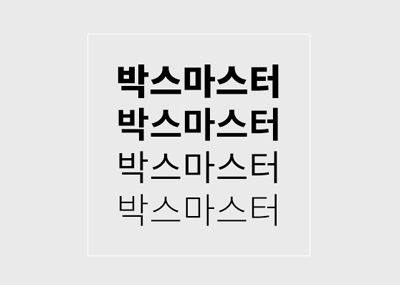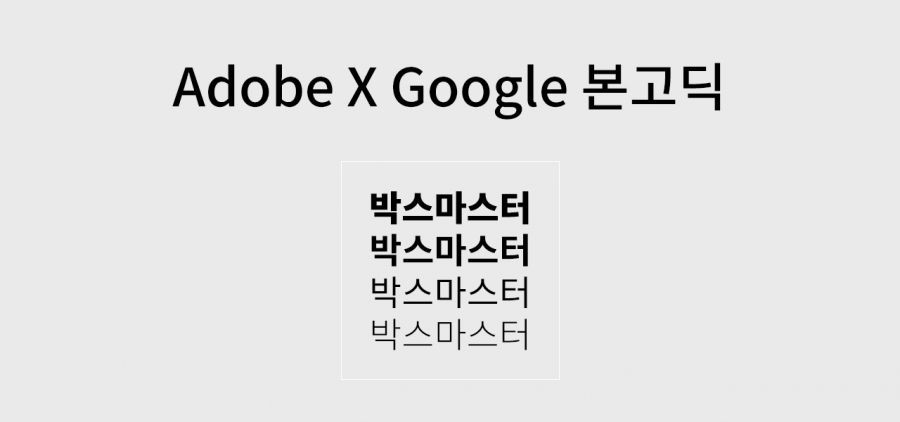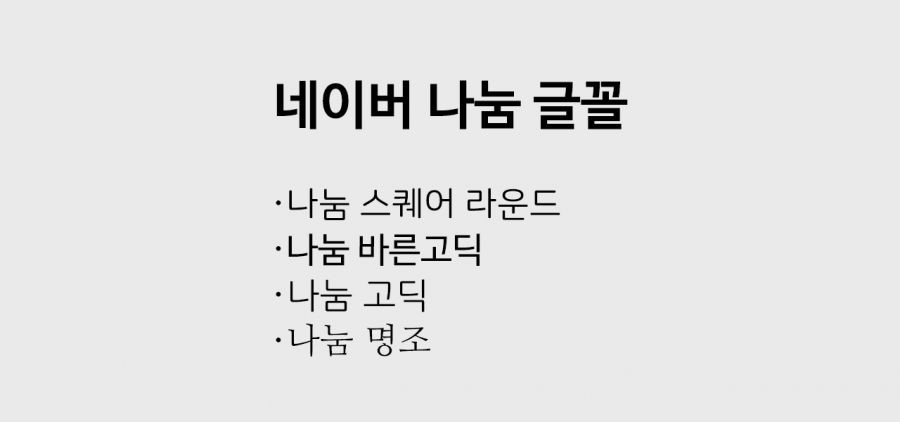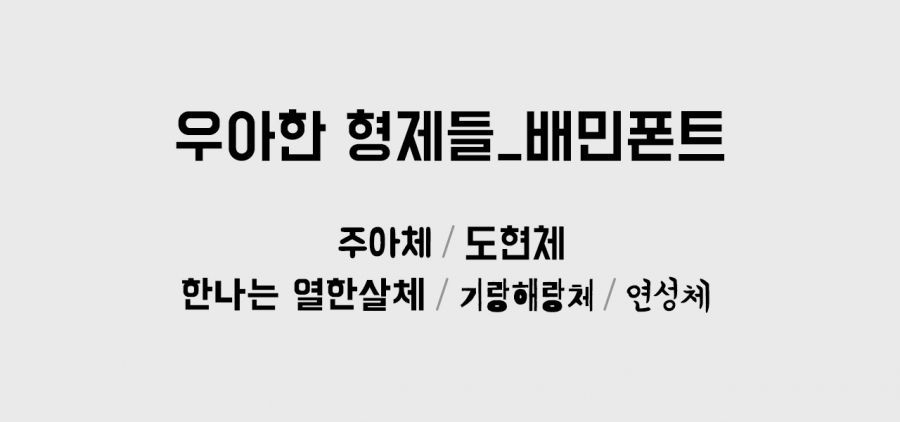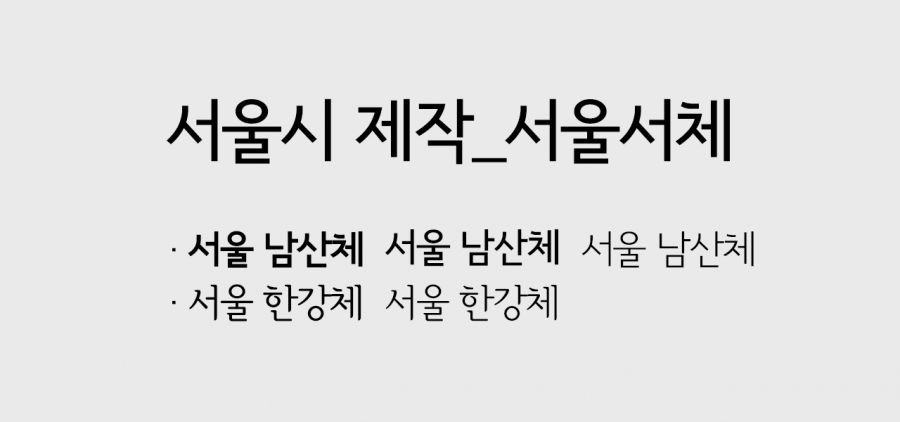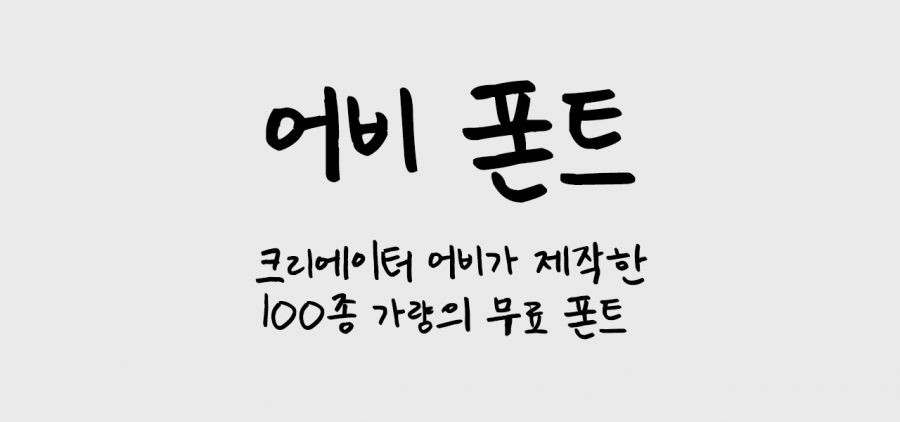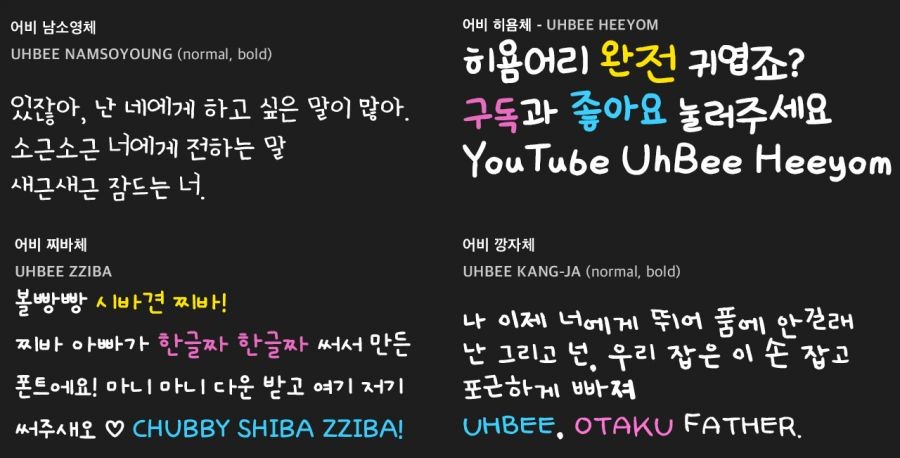
무료 폰트 똑똑하게
활용하기
서체는 브랜드의 인상과 감성을 좌우!
"글씨를 잘 쓰는사람이 마음씨도 곱다" 라는 말 들어보셨나요?
"삐뚤삐뚤한 글씨는 마음가짐도 삐뚤어지게 한다"는 말도 들어보셨을거예요. 디지털 시대가 도래하면서 손으로 글씨를 적을 일이 과거에 비해 현저히 줄어들었지만 우리는 과거부터 예쁘고 보기좋은 서체를 권장하고 찾아왔습니다. 아무리 좋은 글이라도 보는이가 자연스럽게 읽히지 않는다면 말하고자하는 의미가 전달되지 않겠죠?
디자인에서도 어떤 서체를 사용하느냐에 따라 경쾌함,차분함,진지함,신뢰성 등 서체에서 전해지는 감성을 이해하고 적절하게 사용해 대중들에게 기업이 전하고자 하는 바를 명확하게 전달하는것이 좋은 디자인이라고 할수 있겠습니다. 또, 기업이 가진 성격이나 브랜드의 분위기까지도 시각적으로 곧장 전달할 수 있어 올바른 서체를 고르는것이 매우 중요한 부분중에 하나인데요.
무궁무진한 서체의 세계에서 어떤 폰트를 사용해야 할까요? 이번 시간에는 다양한 무료폰트를 제공하는 곳들과, 활용하는 TIP 몇가지를 소개해보고자 합니다.
본고딕
어도비사와 구글사의 합작으로 탄생한 오픈소스 무료 폰트입니다.
한글이 지원된다는 점에서  이미 국내에서도 많은 사랑을 받고 있는데요, 일본어와 중국어까지 지원되어 글로벌하게 사용되면서 유명세를 타고 있습니다. 굵기가 다양하게 겸비된 패밀리 서체로 센스를 겸비한 디자이너라면 굵기 변화만으로도 볼륨감있는 디자인을 완성할 수 있으면서 고딕체 특유의 우수한 가독성까지 겸비해 본문용으로 아주 사랑받고있는 서체라고 할 수 있습니다.
네이버 나눔 글꼴
나눔 글꼴은 네이버가 2008년 10월 9일, 한글날을 맞아 공개한 글꼴입니다.
가장 대중적인 폰트로  무료로 제공되고 있어 더욱  폭넓게 사용되고 있습니다. 나눔스퀘어라운드,나눔스퀘어,나눔바른펜,나눔바른고딕,나눔손글씨,나눔고딕,나눔명조 등 다양한 서체를 지원하면서 오픈 라이센스로 자유롭게 수정하고 재배포가 가능하다는 점에서 부담없이 다양한 사용자가 편리하게 이용하고 있습니다. 오히려 유료로 판매되는것을 금지하고있다고 하는데요. 나눔글꼴 또한 가독성이 높고 깔끔한 느낌이 들어 직관적으로 정보를 전달하고자 할때 사용하면 좋을 것 같습니다. 기존의 다른 고딕체들보다 부드러우면서 둥그런 형태로 딱딱한 이미지를 탈피하고 싶으시다면 나눔체를 사용해보세요. 하지만 너무 흔하게 사용되고 있어 자칫 지루한 느낌이 들수 있어서, 획기적인 디자인을 원하신다면 자제하여 사용하는것이 좋겠습니다.
우아한 형제들 배달의 민족체
"우리가 어떤 민족입니까, ○○야 넌 먹을때가 젤 이뻐" 글자만 봐도 배달의 민족이 떠오르는 우아한 형제들에서 제공하는 무료 폰트입니다.
배달의 민족은 트렌디한 마케팅과 재치와 위트가 넘치는 컨텐츠들로 등장과 함께 대중들의 인기를 순식간에 얻어 지금은 대한민국 대표 배달앱이 되었죠. 그 인기에 보답하듯 배달의 민족에서 제공하는 무료 폰트들은 개성있으면서도 눈길을 사로잡는 서체로 짧고 굵게 강조하기 좋은, 임펙트가 느껴지는 서체라고 볼수 있습니다. 한눈에 봐도 배민체라는것을 알아볼 수 있을 정도로 폰트들의 특징이 강력해 특정 이미지를 벗어나기는 힘드나, 기업에 입장에서는 타이포 브랜딩 사례에서 아주 성공한 입장이라고 할 수 있겠습니다.
야놀자 야체
국내,해외를 아울러 호텔,모텔,펜션등 숙박 관련 예약대행을 해주는 중개업체 야놀자에서 제공하는 야체입니다.
야체 또한 한글날을 기점으로 기업의 로고로 사용되고 있는 야체를 무료로 배포하기 시작했는데요, 사인펜으로 눌러쓴듯한 손글씨 형태로 친근감을 중시하면서 직접 쓴 듯한 느낌으로 리듬감과 자유로움을 부여했다고 합니다. 영어,숫자,특수문자까지 지원된다고 하니 다양한 영역에서 사용하기 좋은 서체입니다. 판촉물의 메인카피나 발표 PPT등 제목이나 주제 키워드에 사용하면 집중도를 한껏 높일 수 있어 포인트 폰트로 활용하기를 야놀자에서 권장하고 추천하고 있습니다.
서울 서체
서울시가 기획,제작하고 배포하는 서울남산체와 서울 한강체입니다.
윤고딕으로 잘 알려진 윤디자인이 개발을 맡아 제작되었다고 하는데요.  서울 남산체는 한국적 곡선을 사용하여 정체성을 표현하고 부드러우면서도 힘있는 디자인입니다. 가독성이 좋으며 먼거리에서도 쉽게 식별되어 눈에 쉽게 띄이는 장점이 있습니다. 또 서울 한강체는 간결하면서도 서체의 고유성을 살린 디자인으로 현대적인 간결함을 표현했다고 하는데요, 서울시에서는 강직한 선비정신과 단아한 여백을 담고 있으며 조형적으로는 한옥의 열림과 기와의 곡선미를 표현하였다고 설명을 덧붙였습니다.
어비 폰트
정형화된 폰트가 딱딱하게 느껴지신다구요? 다양한 기업에서도 수많은 무료 폰트를 제공하고 있지만 또 다른 느낌을 얻고 싶으시다면 여기에 주목해 보세요! 유튜버 크리에이터 어비가 제작한 어비폰트. 손글씨로 제작한 어비폰트는 크리에이터 어비가 수년간 제작해낸 100종 가량의 손글씨 폰트입니다.
삐뚤빼뚤한 느낌의 자연스러운 느낌이 친근함을 느끼게 해주면서 어필하고자 하는 느낌을 서체에서 직관적으로 전달하기 좋아 사용함에 따라 활용도가 무궁무진할 것 같은데요. 유튜브 시장이 넓어짐에 따라 영상제작을 시도하는 일반 대중들이 많아지면서 자기만의 개성을 영상으로 만들어내는 과정에, 다양한 느낌과 감성을 겸비한 어비체가 많은 도움이 될 것 같습니다. 어비체는 상업적으로도 사용이 가능하다고 하니 사용하고자하는 목적에 따라 현명하게 사용하시면 보다 좋은 결과물을 완성해 낼 수 있을것같습니다.
마무리
이밖에도 빙그레체,아리따움체,티몬 몬소리체,미생체,롯데마트의 행복체와 드림체 등 무료로 제공하는 폰트들이 굉장히 많은데요. 단순히 시각적으로 좋아보이는것에 그치지 않고 가독성이나 정보전달 기능에도 충실해야할것을 잊지 말아야 합니다.
실무에서 폰트를 사용하실 때에는 폰트가 가진 성격을 충분히 이해하고 전하고자 하는 목적에 맞도록 현명하게 폰트를 고르는 것이 중요하답니다. 제목은 시각적으로 독창성이 있고 주목성이 좋은 타입으로, 본문은 불편하지 않도록 편안하게 읽히게 디자인해야 좋은 디자인이라고 할 수 있겠습니다.  또 저작권 침해를 우려해 라이센스를 꼭 확인하시는 것도 잊지 않으셔야겠죠?